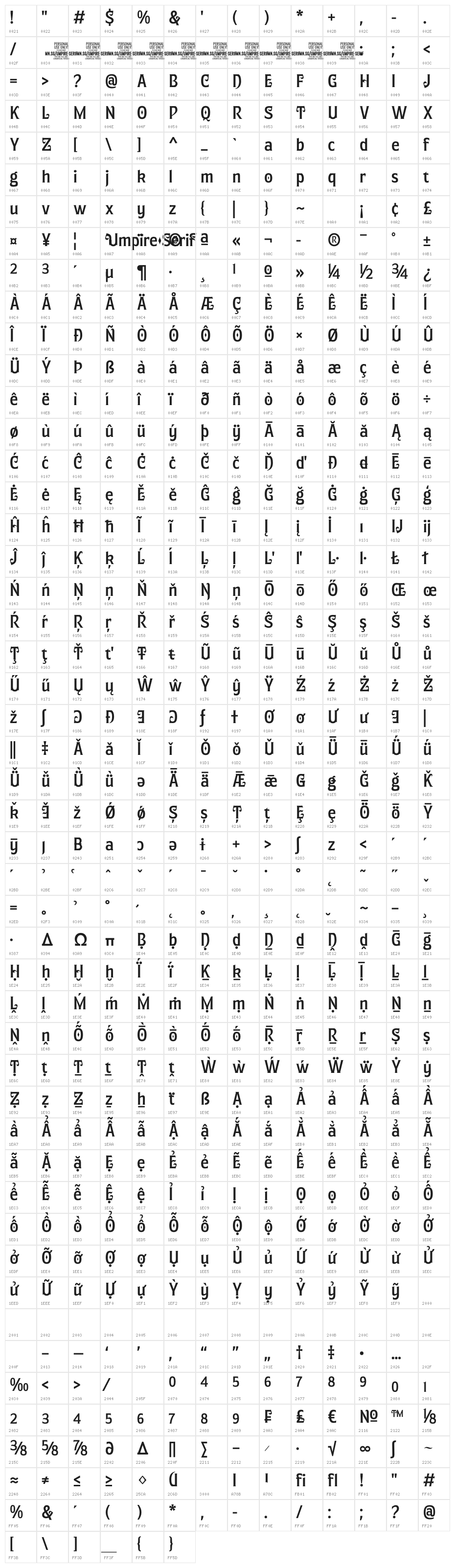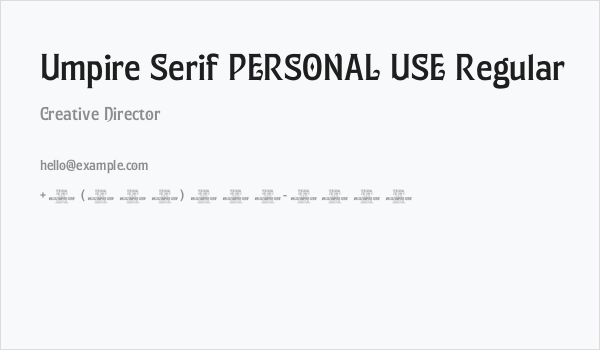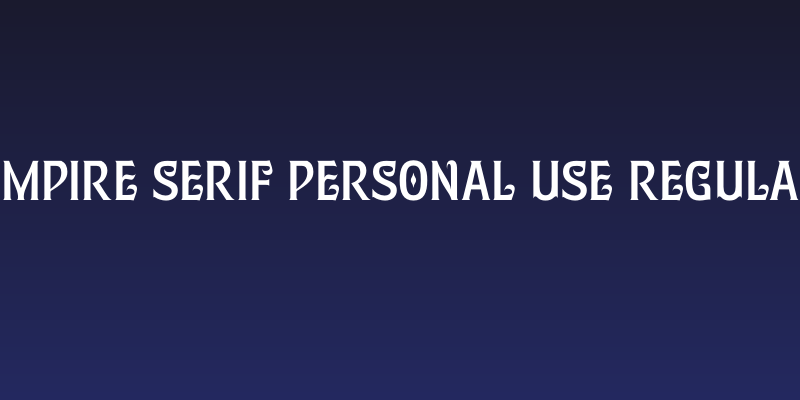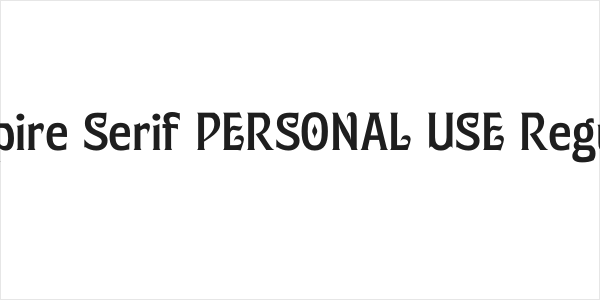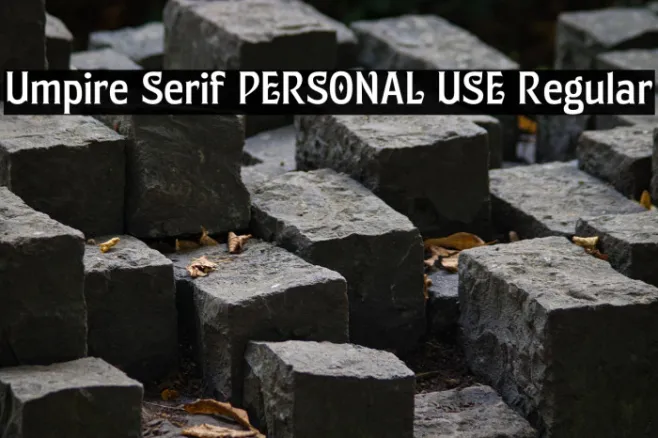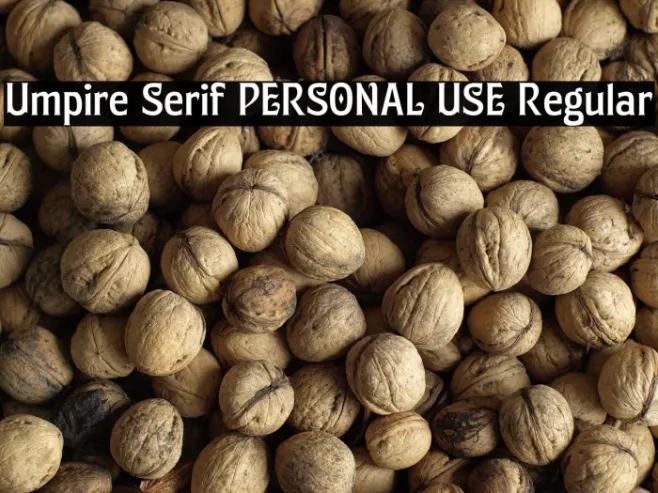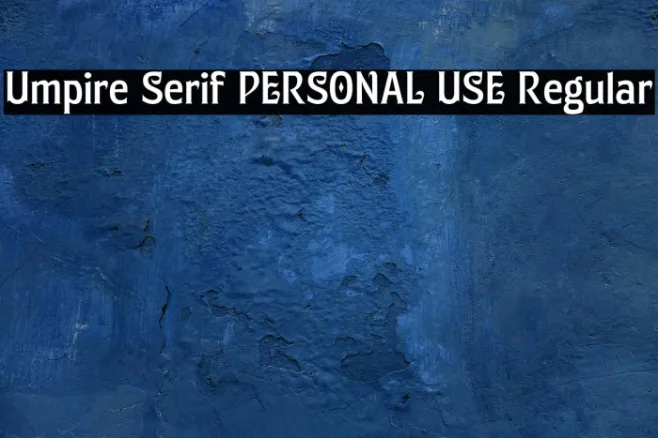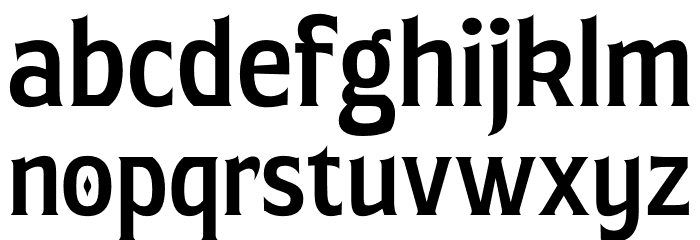
Umpire Serif PERSONAL USE Regular Font
✎ Serif
| Gesamtstil | Modern, Decorative |
| Vorgeschlagene Projekte | Ideal for branding, poster design, book covers, and any project requiring a bold, decorative serif font. |